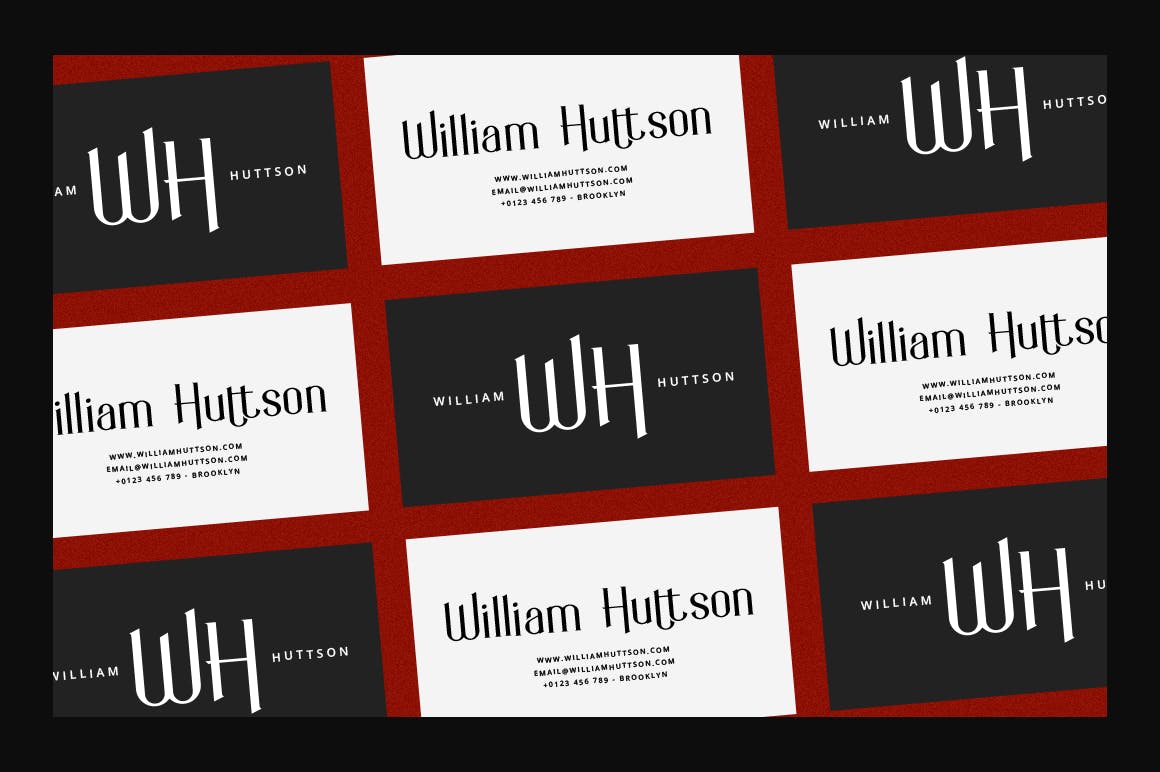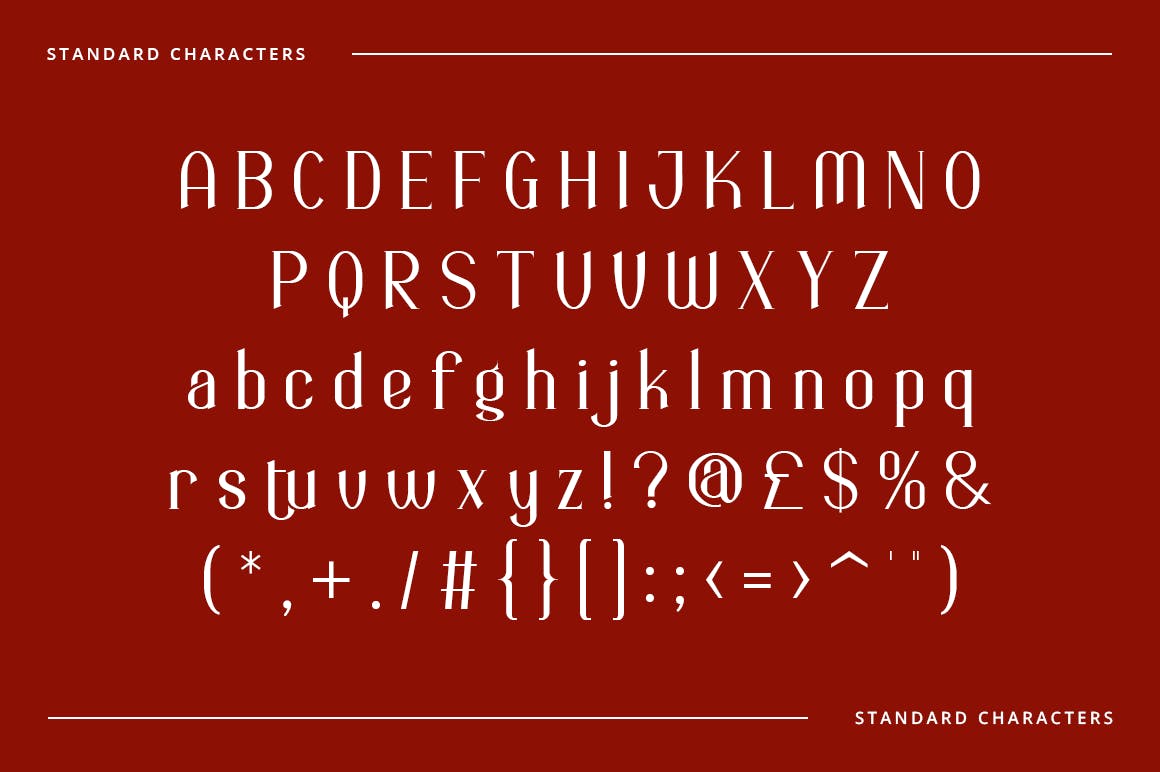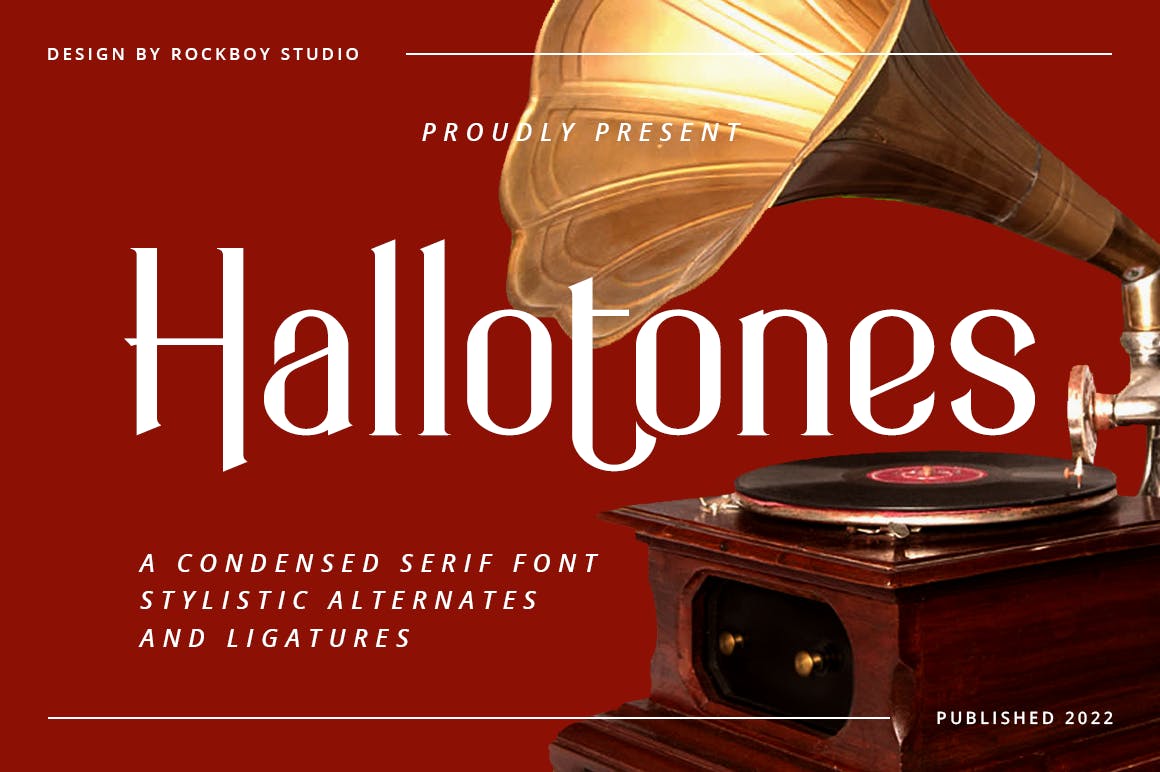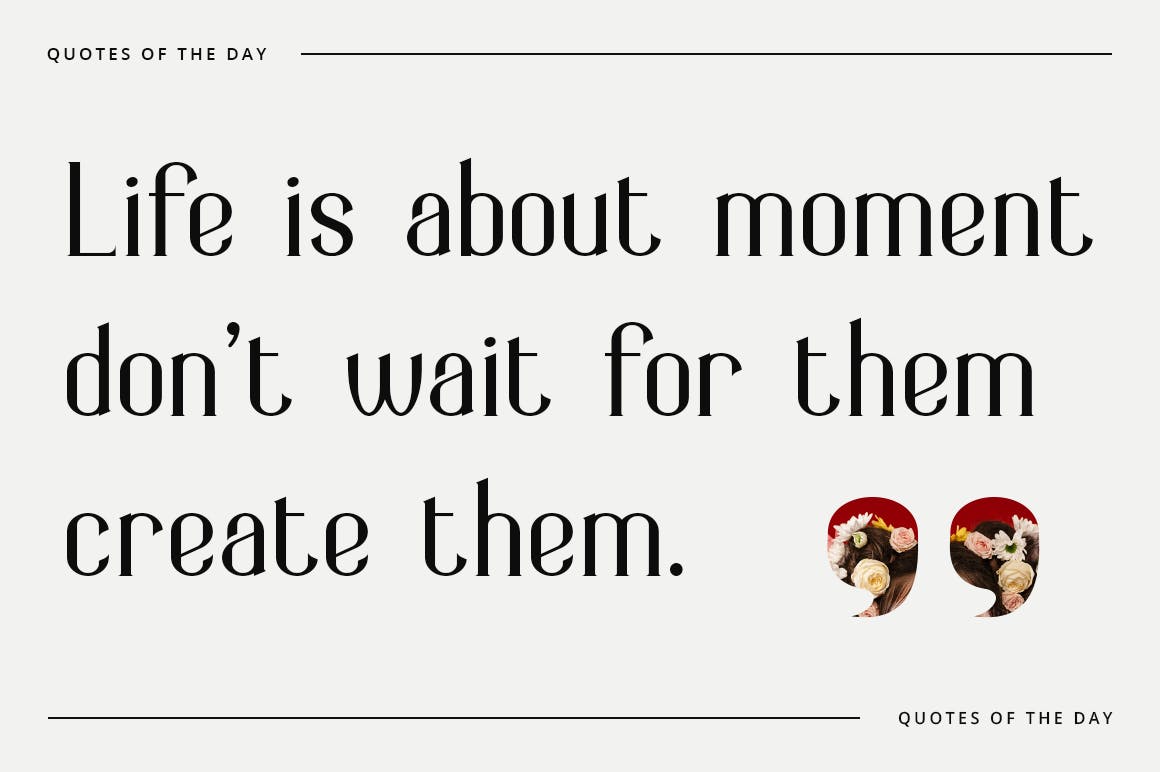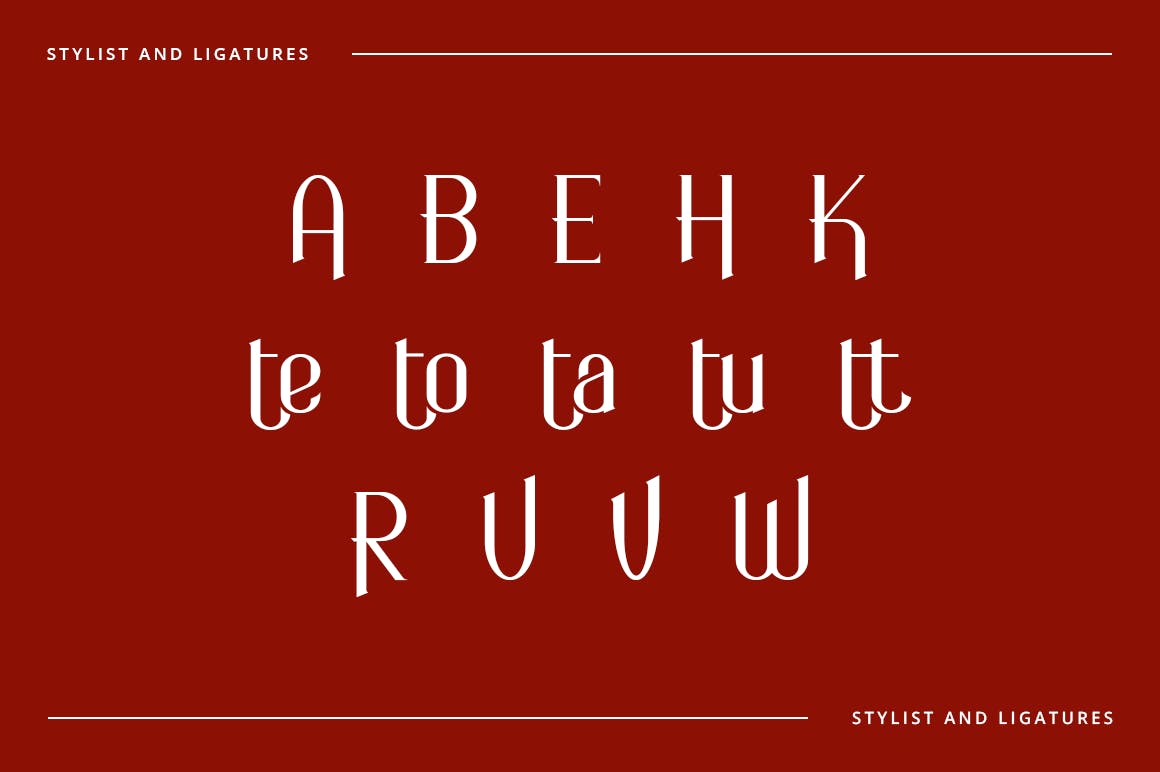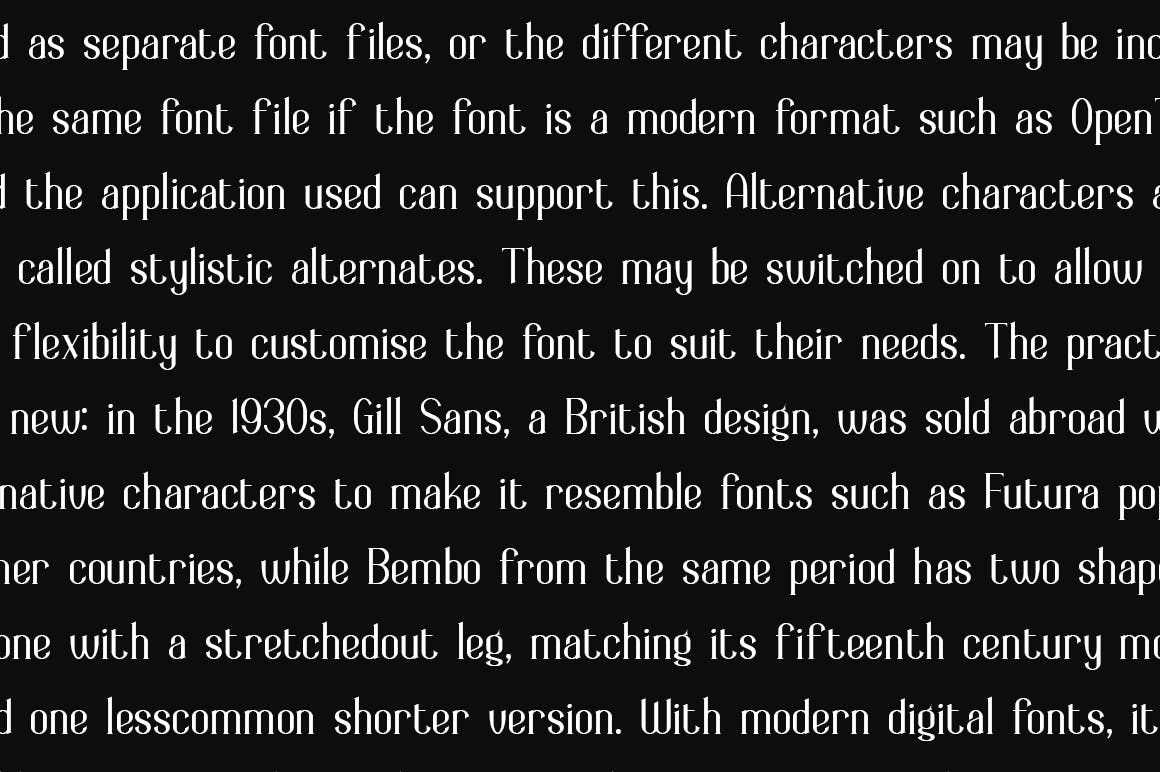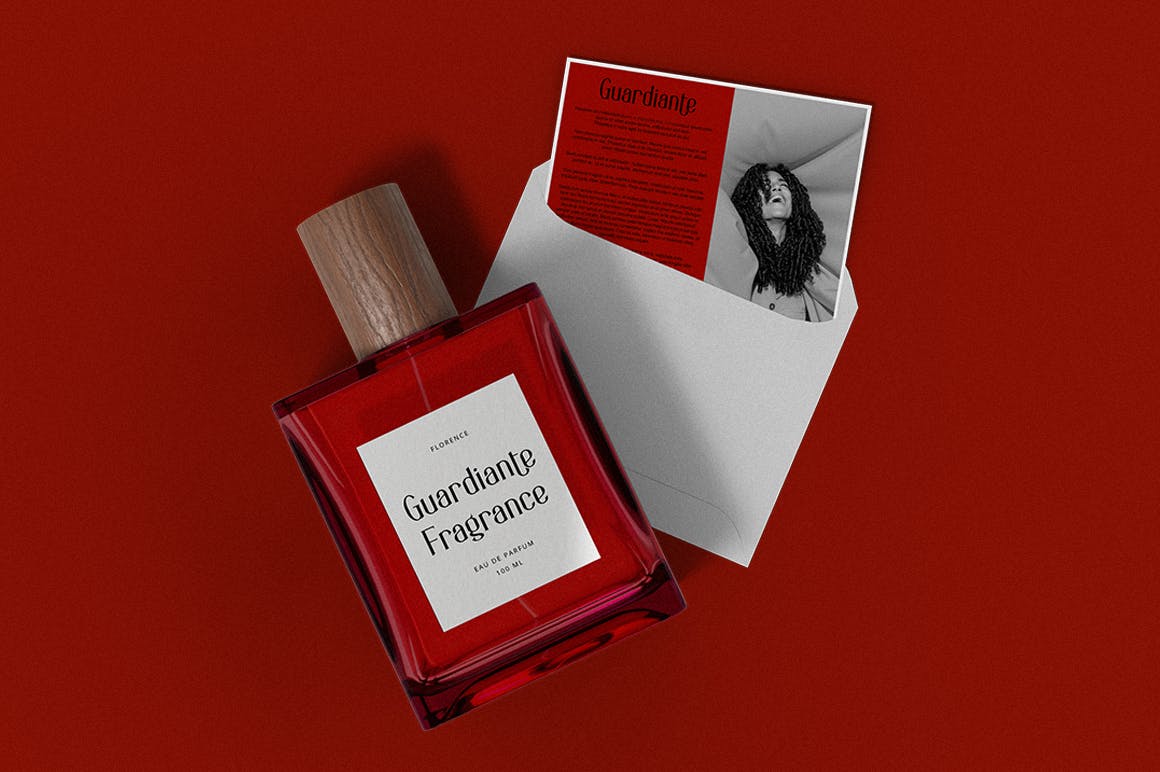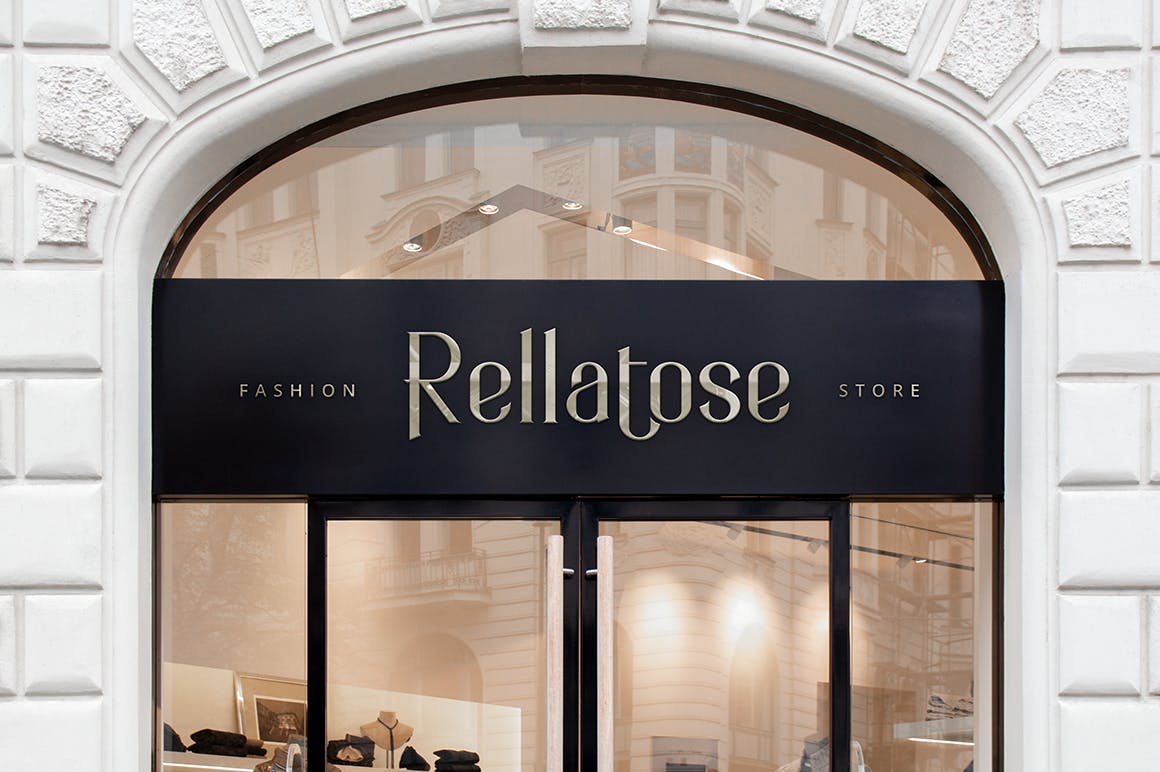
هالوتونز یک فونت سریف متمایز، جسور و اصیل است. این فونت با طراحی ماهرانه خود میتواند به یکی از انتخابهای محبوب شما تبدیل شود و هر یک از ایدههای خلاقانهتان را به بالاترین سطح برساند!